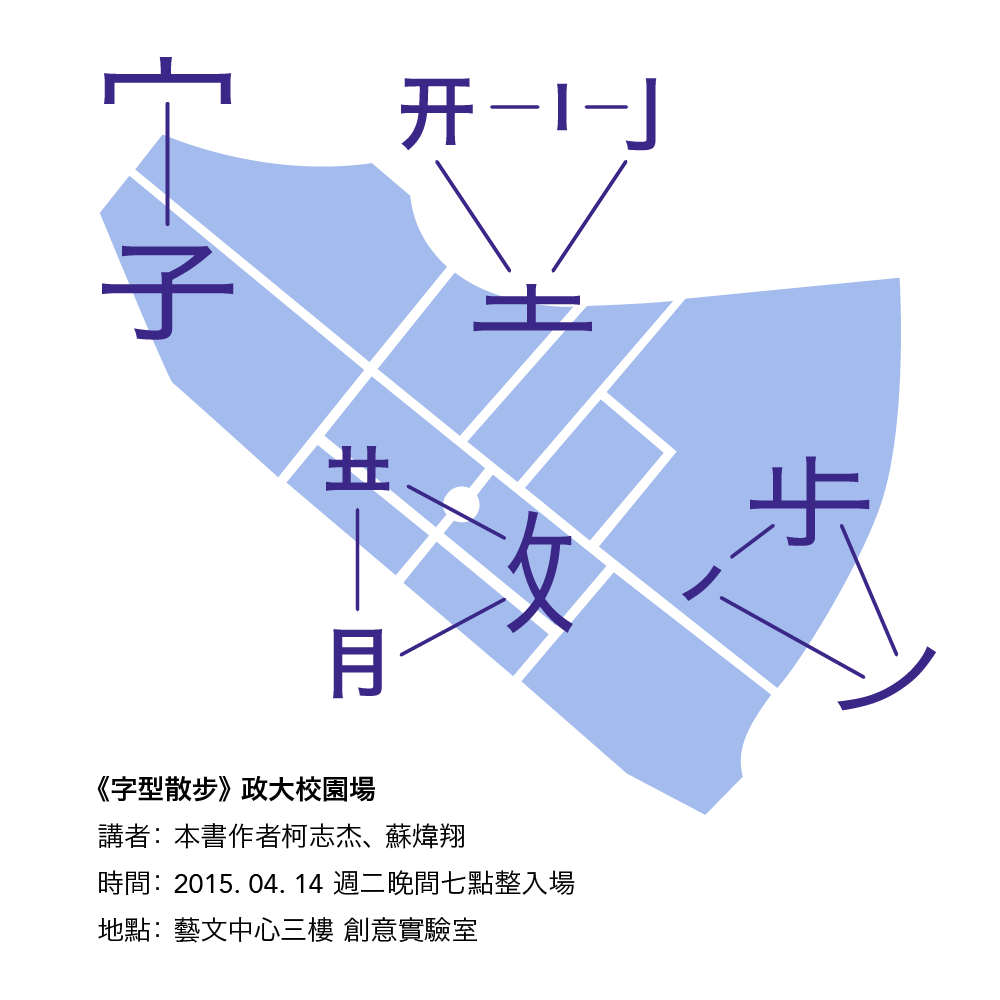
關於《字型散步》
《字型散步》是第一本以台灣生活議題為中心的中文字型專著。關於字型,我們用得很多,但知道得卻非常少。其實字型不僅是平面設計的核心元素,還與一國的文化與歷史息息相關。《字型散步》並不教導如何正確使用字型,而是告訴讀者中文字型背後的故事。為什麼台灣的夜市章魚燒會這麼喜歡使用「勘亭流」?明體原來是從楷書來的嗎?為什麼不要一直使用康熙字典體呢?透過解析這些議題,讓讀者輕鬆入門字型的學問。
關於講者
柯志杰|「字嗨」社團發起人,為中文字型提供一個自由討論的場地。熱衷於探尋中、日文各類印刷字體的由來與差異,也涉入中文字型編碼、造字技術,發表有 Unicode 補完計劃。
蘇煒翔|「字戀」專頁主編,在 justfont 負責社群媒體經營。從前未接觸字型與視覺傳達相關領域,相關知識與技能都是工作兩年間自學而成。蘇煒翔目前也是政大數位內容學程碩士生。
講者: 本書作者柯志杰、 蘇煒翔